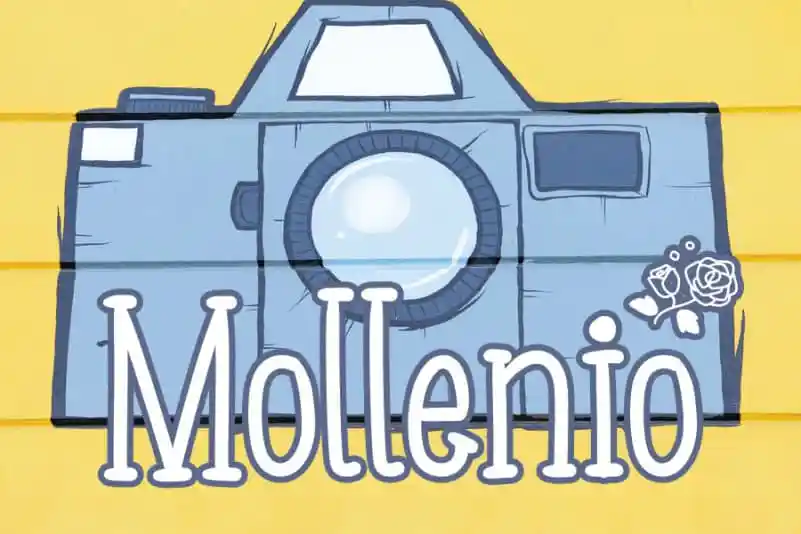
Mollenio Display Font é uma elegante fonte de display que traz simplicidade ao design gráfico. Seu equilibrado estilo e proporções bem definidas a tornam adequada para diversos tipos de projetos visuais, seja para criação de materiais publicitários, artigos informativos ou até mesmo gráficos corporativos. Perfeita tanto para um design moderno quanto para aqueles que buscam um ar mais vintage, Mollenio Display é uma excelente escolha para quem busca uma fonte de display serif sem ser tradicionalmente complexa. Com suas linhas finas e claras, esta fonte oferece um acabamento clean e sofisticado perfeito para qualquer projeto.